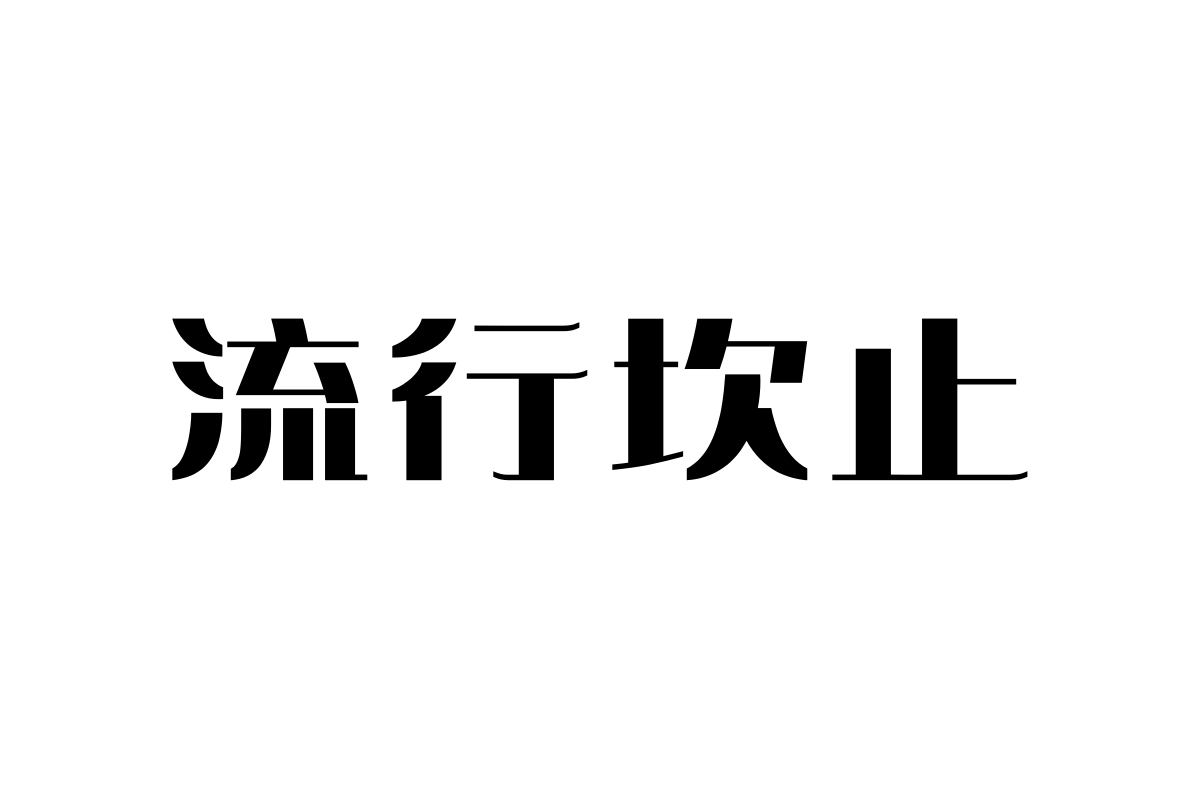
黑体是一种常见的中文字体,由微软公司开发。它的特点是字形粗壮,线条粗犷有力,给人一种强烈的视觉冲击力。黑体的使用非常广泛,无论是在印刷品、广告、网页设计还是其他各种媒介中,都可以看到它的身影。
由于其独特的视觉效果和广泛的应用,黑体成为了现代设计中不可或缺的一部分。无论是设计师还是普通用户,都可以在需要的时候选择使用黑体来表达自己的观点和情感。